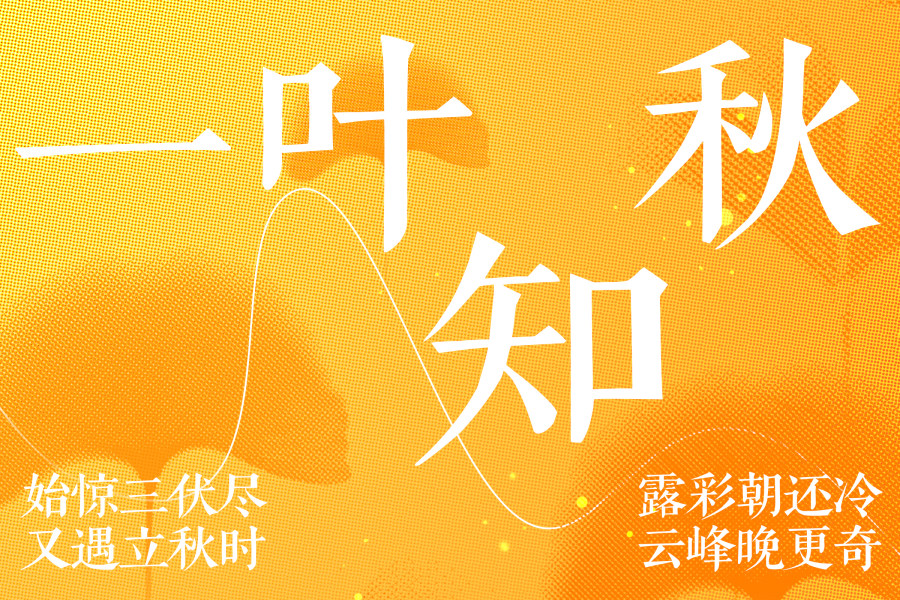
兼具古典和现代特点的精品商用字体——Aa古典刻本宋
《Aa古典刻本宋》是一款独具特色的字体,汲取了康熙字典内文宋体的精髓,并经过现代化数字处理,焕发出简洁锐利的新生命。这一字体的应用领域广泛,凭借其独特的特点,成为许多设计项目的首选。
其最显著的特点是融合了古典与现代的美感。字体保留了古雅书香,同时注入了现代化的精致,使得它适用于书籍排版、文学作品、古典文化展示等领域。在印刷品和电子媒体上,它能够传达出深厚的文化底蕴,同时保持清晰的可读性,给读者带来愉悦的阅读体验。